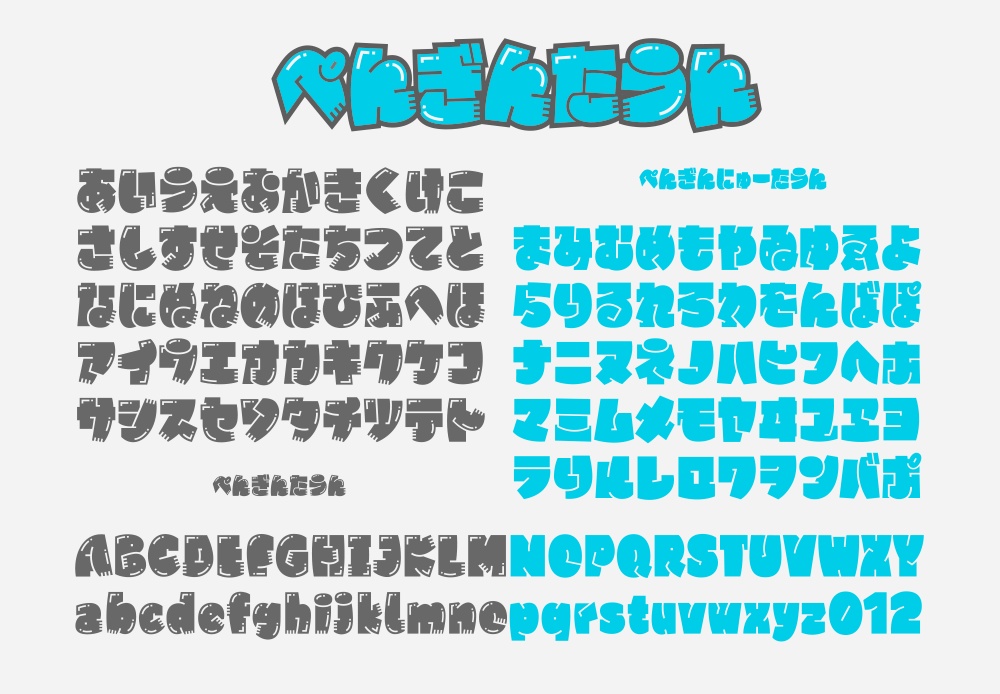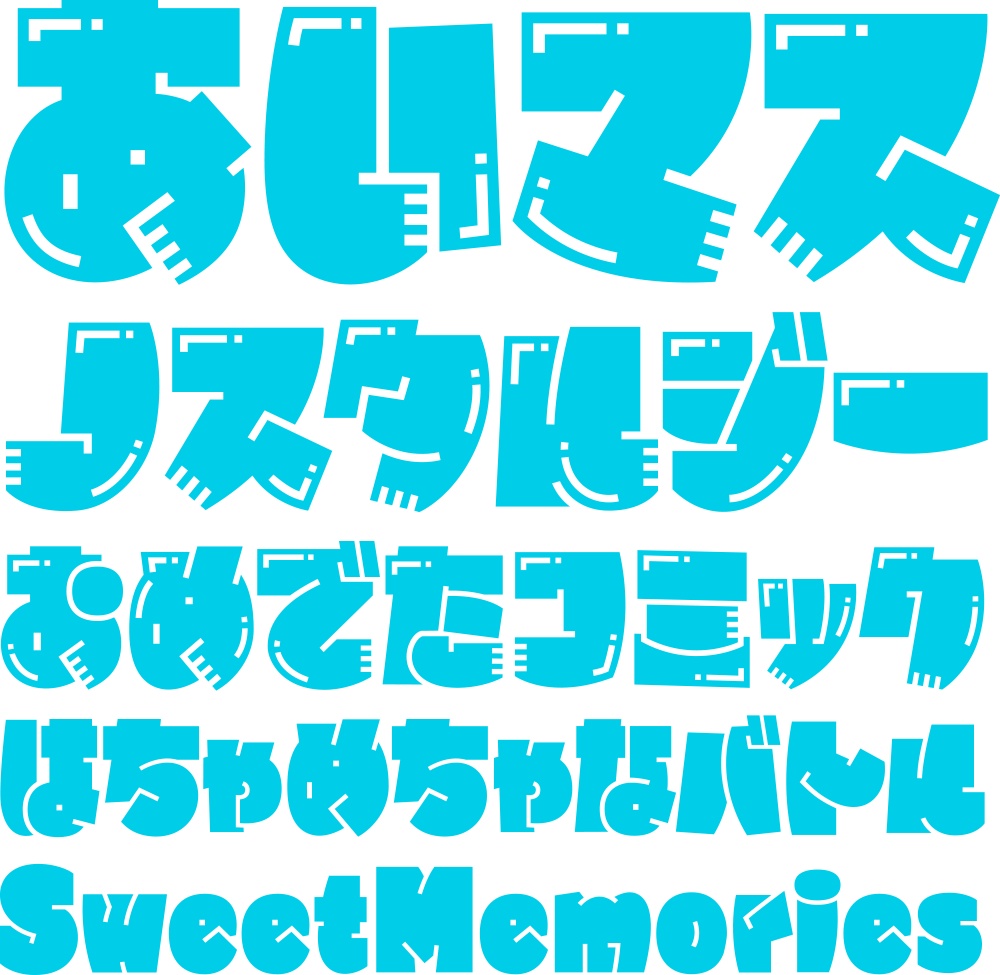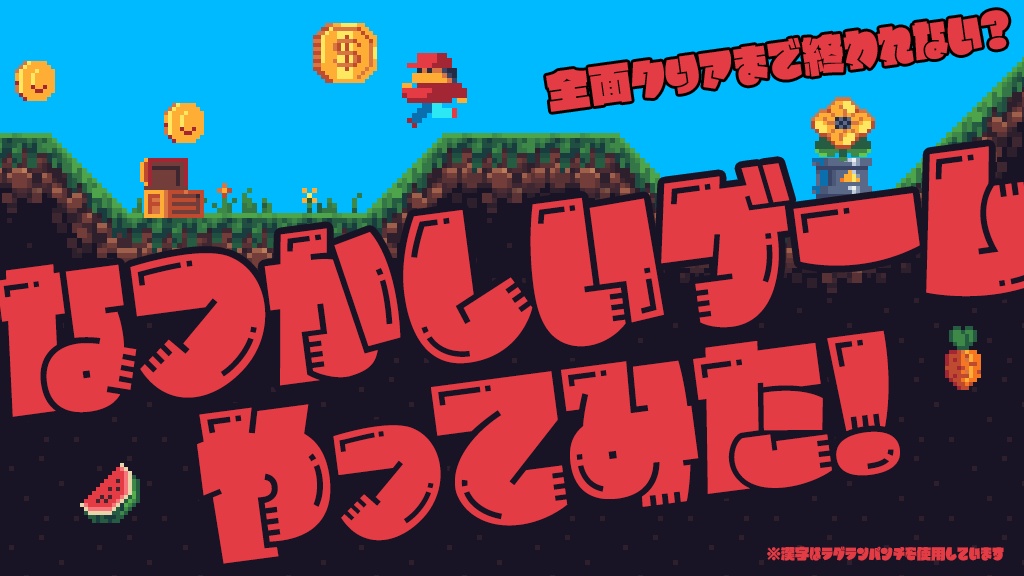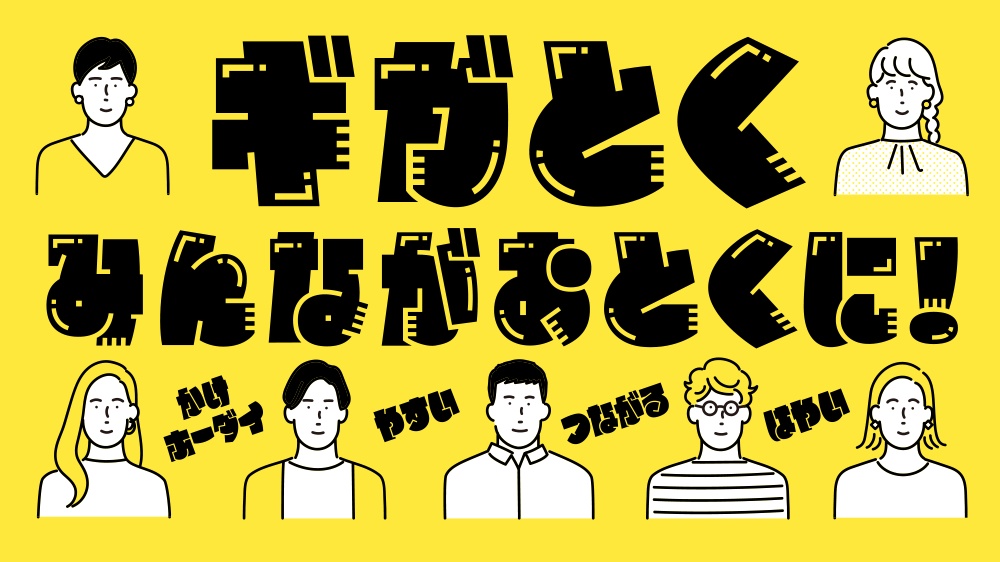
ぺんぎんたうんフォント(3フォントSET)
ぺんぎんたうん 80年代風の超極太POP体。 少し縦長でインパクトとキュートさを兼ね備えたフォント。ポップ体なのに和風のひげ文字のような部分は、個性的でコミカルな表現を可能にします。ロゴや映像のタイトルとして大活躍間違い無しのフォントです。 ■動作環境 Mac:システム/OS X対応(10.x)〜最新のOS X Windows:OS/日本語版Windows2000、XP、VISTA、Windows7、Windows8、Windows10 フォント形式:OpenTypeフォント、TrueTypeフォント ※Adobeイラストレーター、フォトショップはもちろんのことWindows用ワード・エクセル等でもご使用になれます。 1商品(1ライセンス)につき1ユーザー1PCのみがご利用いただけます。複数人で使用する場合は人数分をご購入ください。 ■安心して使えるロイヤリティフリーの書体 あらゆる商用・デザイン用途(印刷物・ゲーム・アプリ・映像・動画・ロゴ・同人作品)に使用できる、商用申請の必要のないロイヤリティフリーの書体になります。文字の加工・変形も可能です。ご安心ください。 ■グリフ 全410字(アルファベット、ひらがな、カタカナ、約物の一部)。漢字は収録されていないのでAdobe Illustrator、Adobe InDesignなどのアプリケーションで任意の漢字のフォントを組み合わせてご利用ください。 ■文字デザイン ツヤ処理とひげ文字処理が特徴の「ぺんぎんたうん」とシンプルなデザインの「ぺんぎんにゅーたうん」使い分けることで印象の異なるデザインが作れます。濁点・半濁点は個性的なデザインになっておりロゴ・見出しで目を引きます。アルファベットは日本語に合わせたデザインで、ディセンダーの位置も高くなっておりロゴにした時にまとまり感があります。縁取り文字の「ぺんぎんたうんポップ」はPOPに使いやすいデザインになっています。